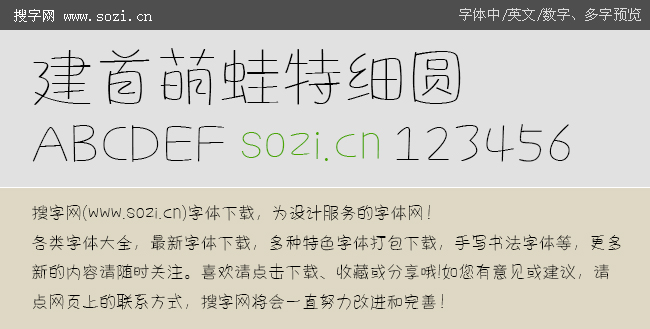
建首萌蛙特細(xì)圓
搜字網(wǎng)提供一款建首萌蛙特細(xì)圓中文字體下載,建首萌蛙特細(xì)圓是一套卡通風(fēng)格的POP字體。字體筆畫簡潔醒目,字形為卡通風(fēng)格,充滿童趣,看上去非常可愛。適合兒童包裝設(shè)計、海報設(shè)計、廣告設(shè)計等應(yīng)用。